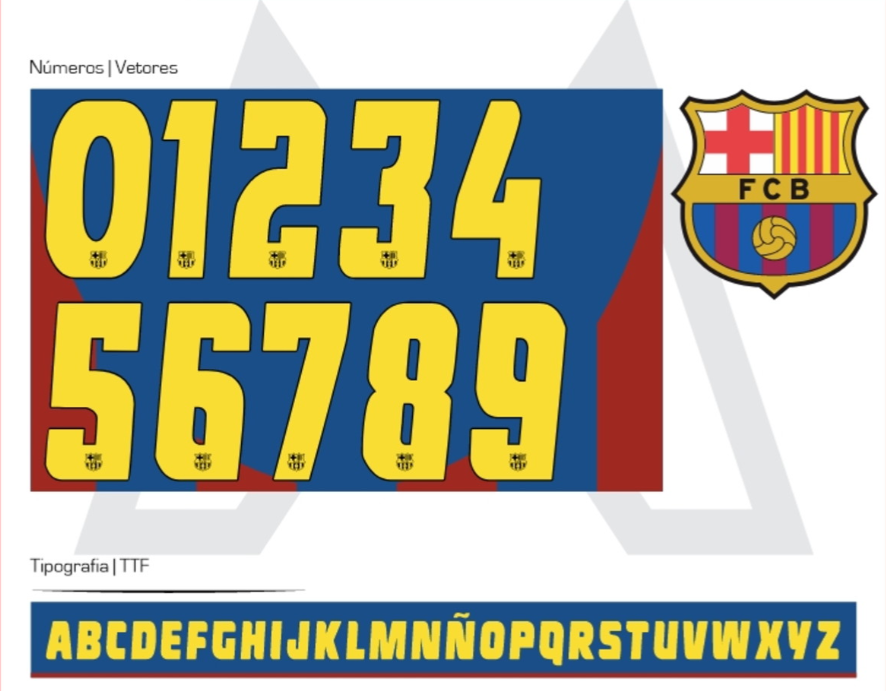
Poucas camisas na história do futebol pesam tanto quanto o manto do FC Barcelona da metade dos anos 2000. Estamos falando da época mágica em que Ronaldinho Gaúcho encantava o mundo, Lionel Messi dava seus primeiros passos e o time conquistava a Europa.
Para os designers, colecionadores e apaixonados por futebol retrô, trazemos hoje o arquivo da fonte oficial utilizada pela Nike nas temporadas 2005/06 e 2006/07. Essa é a tipografia que estampa a camisa do título da Champions League de 2006 em Paris, um item obrigatório no seu acervo de assets.
Estilo Visual e Identidade
A tipografia criada pela Nike para este período do Barça reflete a transição do clube para uma era mais moderna, mas sem perder a classe.
Diferente das fontes mais quadradas e industriais usadas atualmente, a fonte de 2005-2007 possui bordas levemente arredondadas e uma estrutura sólida. Nos uniformes titulares Blaugrana, ela ganhava destaque na cor amarela (dourada), criando um contraste perfeito com o azul e grená. Já nos icônicos uniformes “verde limão” e laranja da época, a fonte aparecia em preto ou azul, garantindo leitura rápida e estilo inconfundível. É a escolha certa para quem quer recriar a mística do “Joga Bonito”.